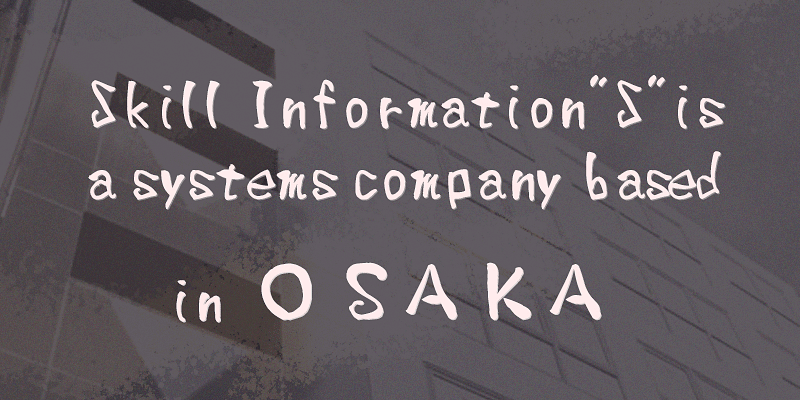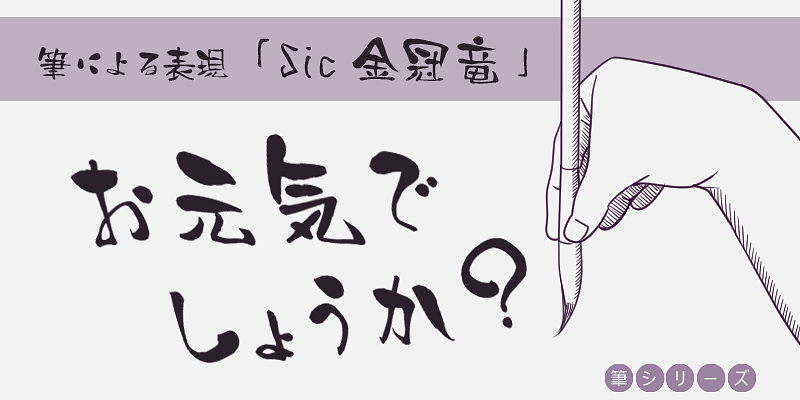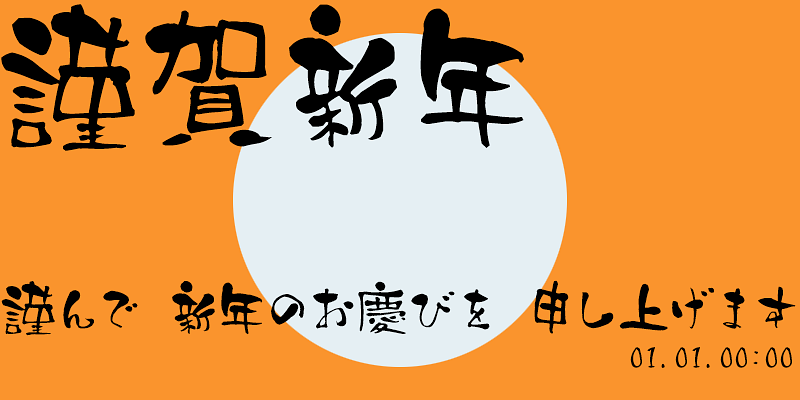
Les polices de caractères manuscrites au pinceau de Hideo Miyagi se caractérisent par des coups de pinceau uniques qui allient force et délicatesse. Les caractères gras sont puissants et percutants, tandis que les caractères fins créent une expression délicate et nuancée. La variation naturelle de la pression du pinceau apporte de la chaleur et une excellente lisibilité. Ses créations typographiques harmonisent l’esthétique japonaise traditionnelle avec le design moderne, ce qui les rend adaptées à un large éventail d’utilisations, tels que les menus d’izakaya, les affiches et les vignettes de YouTube. Les écritures au pinceau, riches en émotions, de Miyagi apportent à la fois force et chaleur à toutes les créations.
Connue pour son rôle dans le développement de logiciels, en particulier dans le secteur des soins de santé, la société Skill Information “S” s’est retrouvée sur le marché des polices par le biais d’une collaboration avec Techno Advance Co, Ltd, en 2007.